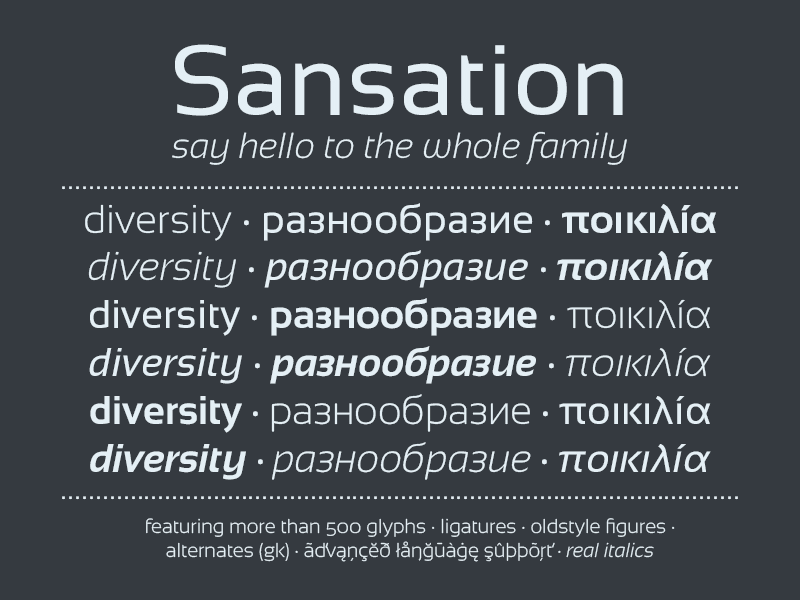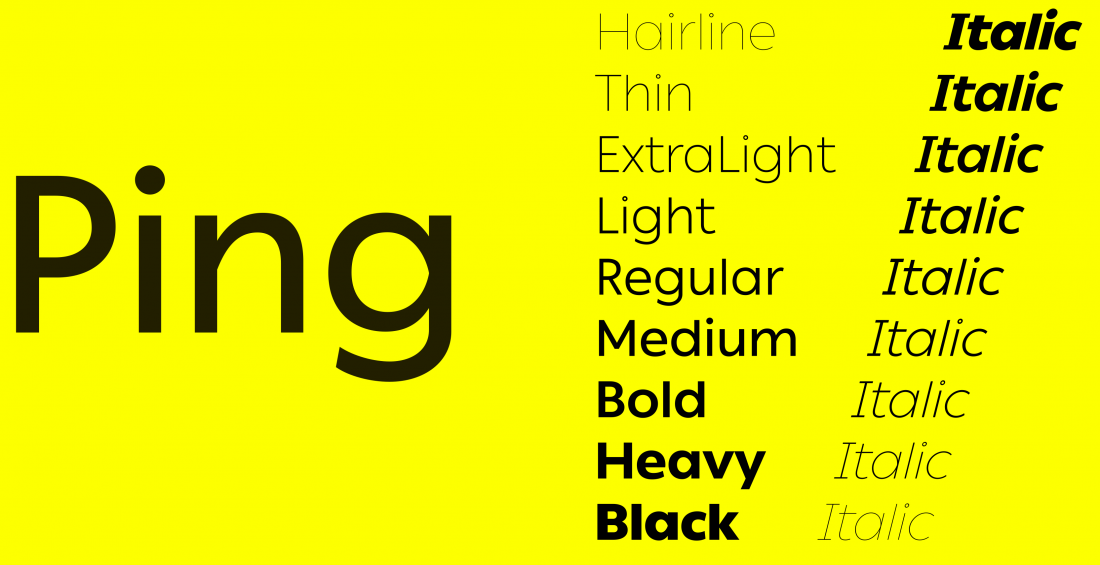
Лучшие шрифты для бизнеса в 2020 году cкачать бесплатно
Если вы ищете идеальный шрифт для логотипа, визитной карточки, канцелярских товаров или любого другого бренда для корпоративного бизнеса, вы попали в нужное место.
В этом посте мы представляем вам коллекцию лучших шрифтов, которые вы можете использовать с дизайнами, связанными с бизнесом и корпоративными брендами.
Независимо от того, делаете ли вы рекламный проспект, плакат, вывеску или ищете шрифт для вашего бренда, в нашей коллекции вы найдете все виды шрифтов, которые можно использовать в различных дизайнерских проектах и целях.
Media Times
Этот элегантный и профессиональный шрифт является отличным выбором для создания фирменного стиля или практически любого типа бизнеса или корпоративного дизайна.
Современный дизайн этого шрифта также гарантирует, что ваш бренд и бизнес-дизайн будут оставаться актуальными в течение длительного времени.
Nordhead
Nordhead — это чистый и профессиональный шрифт, который вы можете использовать для разработки любых деловых и корпоративных проектов.
WALTER
Walter — это креативный бизнес-шрифт с уникальным дизайном, который делает его идеальным для дизайна брендов класса люкс и высокого класса. Шрифт поставляется в 5 различных весах от тонкого до тяжелого. Он также доступен в версии веб-шрифтов.
Monolith
Monolith — это ультра-минималистичный шрифт с тонким буквенным дизайном. Этот шрифт больше всего подходит для современного бизнеса и креативных агентств для создания логотипов, визиток и дизайна сайтов. Шрифт включает многоязычную поддержку и доступен в нескольких размерах.
Murphy Sans
Murphy Sans — это элегантный шрифт с дизайном без засечек, который на самом деле выглядит как шрифт с засечками. Это дает ему уникальный профессиональный вид. Этот шрифт идеально подходит для создания всевозможных деловых и корпоративных дизайнов.
Gamine
Gamine — это бесплатный шрифт с уникальным дизайном букв. Шрифт поставляется с набором альтернативных символов и лигатур, которые вы можете использовать, чтобы добавить уникальный штрих к вашему дизайну. Это совершенно бесплатно для ваших личных и коммерческих проектов.
Houston
Houston — это пара элегантных бизнес-шрифтов, которые поставляются как со шрифтами со шрифтами, так и со шрифтами с засечками, которые вы можете комбинировать для создания стильного делового и корпоративного дизайна. Шрифты также доступны в легком и наклонном дизайне.
BERLIN Rounded
Berlin — это красивый шрифт без засечек с набором закругленных символов. Этот шрифт идеально подходит для создания логотипов, баннеров и заголовков сайтов для современных стартапов и корпоративных агентств.
Metrisch
Metrisch — это креативный бизнес-шрифт с минималистичным тонким дизайном. Этот шрифт наиболее подходит для создания профессиональных и корпоративных логотипов, канцелярских товаров, листовок и многого другого.
Шрифт также имеет стилистические варианты.
Batisde
Batisde — это пара современных шрифтов, которые содержат как шрифты со шрифтами, так и шрифты с засечками, которые можно бесплатно использовать в личных проектах. Эта пара шрифтов идеально подходит для создания люксового бренда и современного корпоративного дизайна.
RAXTOR
Raxtor — это еще один профессиональный шрифт, который вы можете использовать для создания различных деловых и корпоративных дизайнов.
Orion Pro
Orion Pro — это современное семейство шрифтов, которое включает в себя 12 различных шрифтов от светлых до черных, а также курсив. Шрифт имеет узкий дизайн без засечек, что делает его пригодным для оформления заголовка и основного текста.
Hasty
Hasty — элегантный бизнес-шрифт со стильным дизайном сценария. Этот шрифт наиболее подходит для создания визиток, логотипов и этикеток для современных компаний и брендов.
Rockyeah
Этот креативный шрифт имеет современный дизайн с набором символов с необычным дизайном. Поскольку это жирный шрифт с прописными буквами, он лучше всего подходит для создания заголовков и заголовков для профессиональных дизайнов.
Monometric
Monometric — это смелый бесплатный шрифт с заглавными буквами, который лучше всего подходит для создания заголовков и заголовков вашего бизнеса и профессионального дизайна. Он также включает цифры и знаки препинания.
Rolves
Rolves — это элегантный бесплатный шрифт, который вы можете использовать для создания всех видов корпоративного и делового дизайна, включая логотипы, визитки, канцелярские товары и многое другое. Это бесплатно для личных проектов.
Bambi
Bambi — это коллекция красивых шрифтов с креативным дизайном кисти. Изящный дизайн этого шрифта делает его идеальным для женских брендов и бизнес-дизайнов, таких как логотипы, этикетки и флаеры.![]()
Garde — это уникальный шрифт, созданный специально для создания логотипов для роскошных и современных предприятий. Шрифт поставляется в нескольких форматах, включая веб-версию шрифта шрифта.
Milano
Milano — это креативный бизнес-шрифт со смешанным дизайном ретро-футуристических элементов. Шрифт идеально подходит для создания логотипов, этикеток и значков для брендов класса люкс, модных брендов и агентств.
Хотя эти стили шрифтов, вероятно, не подходят для непрерывного чтения, их сочетание с другими шрифтами — отличный способ повысить узнаваемость вашего бренда.
Выберите лучший шрифт для себя!
Выбор правильного шрифта может быть сложной задачей, особенно когда есть из чего выбрать. Однако этот процесс вовсе не должен сводиться к следованию или противодействию тренду.